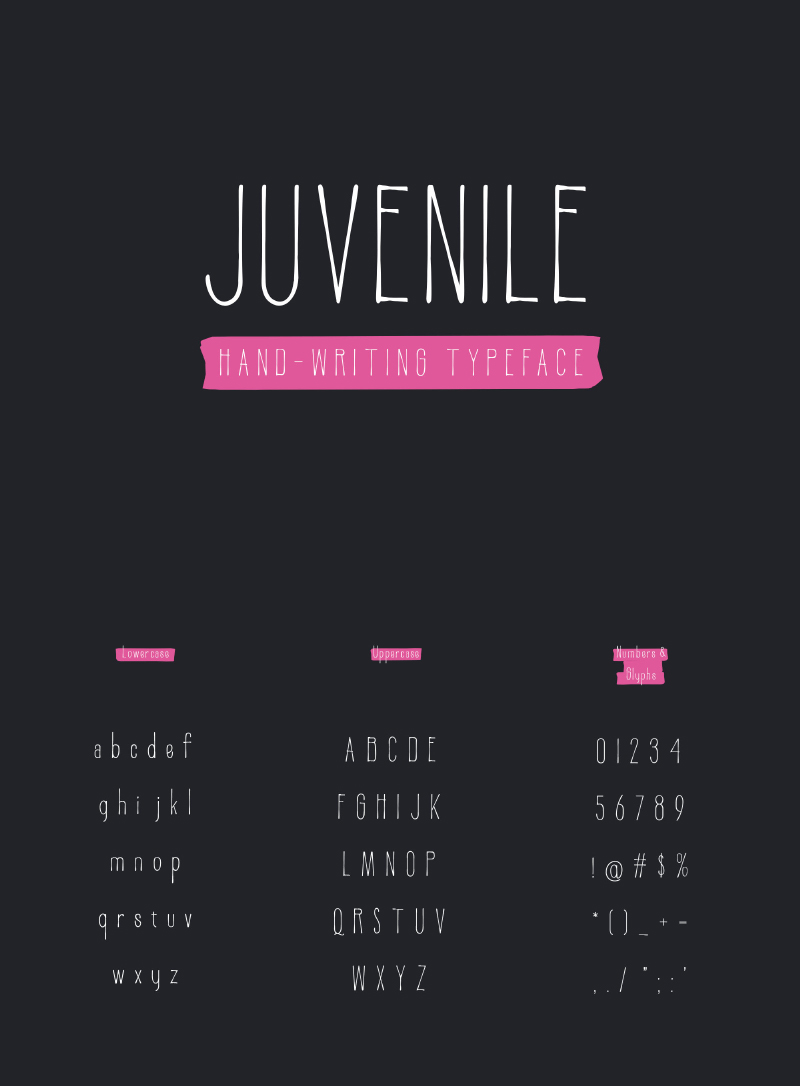
Шрифт - Juvenile
Juvenile - гротескный шрифт, созданный с эффектом рукописных символов, который придает гармонию и приятность вашему типографическому дизайну. Шрифт можно использовать на футболках, кружках, плакатах, цитатах и многом другом.